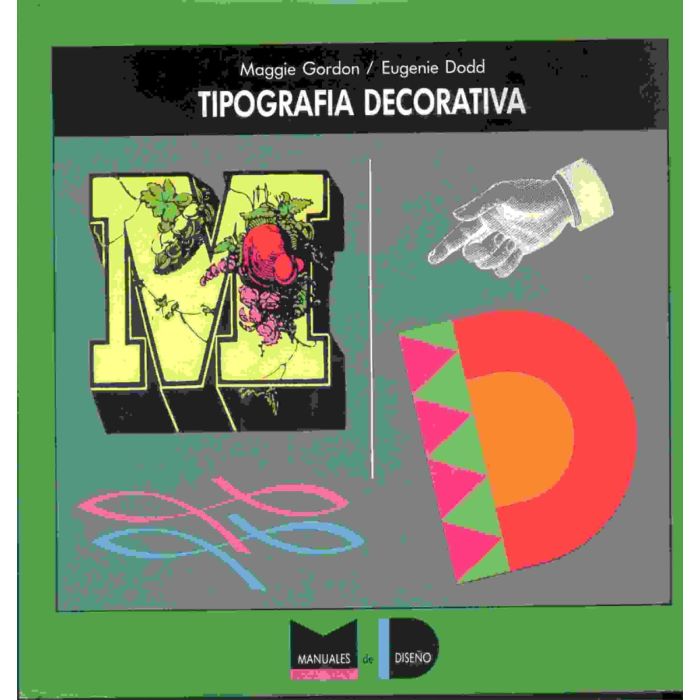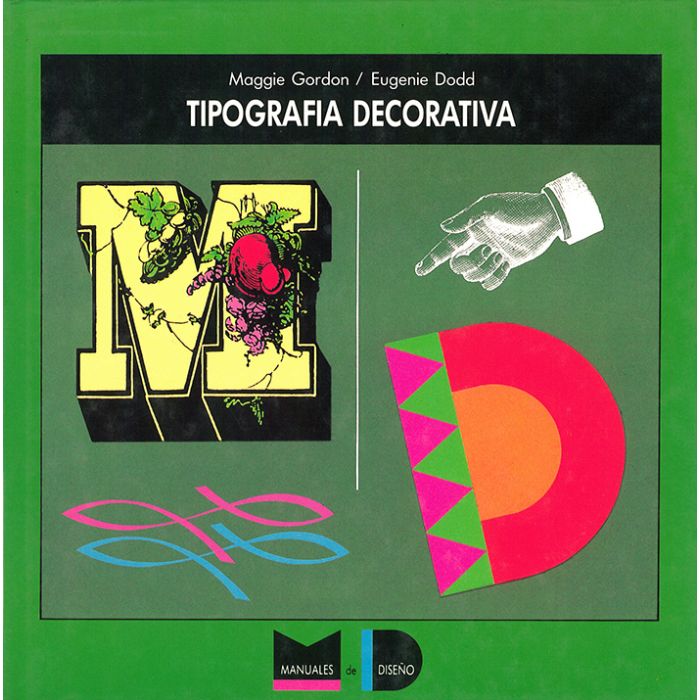
Tipografía decorativa
La tipografía es una de las primeras prácticas del diseño que se puede dominar y tambien es una de las más difíciles. Un conocimiento claro de sus posibilidades es esencial si se quiere sacar el máximo partido de cualquier diseño.
Tiografía decorativa muestra precisamente cómo introducir rúbricas y adornos para dar un toque de estilo individual y de personalidad a un determinado tipo de letra. Se cubren todas las posibilidades, desde la introducción de una simple línea hasta el uso de mayúsculas decarativas y el potencial de los sombreados y negativos, y se muestran los espectaculares efectos de diseño que se pueden producir.
La tipografía es una de las primeras prácticas del diseño que se puede dominar y tambien es una de las más difíciles. Un conocimiento claro de sus posibilidades es esencial si se quiere sacar el máximo partido de cualquier diseño.
Tiografía decorativa muestra precisamente cómo introducir rúbricas y adornos para dar un toque de estilo individual y de personalidad a un determinado tipo de letra. Se cubren todas las posibilidades, desde la introducción de una simple línea hasta el uso de mayúsculas decarativas y el potencial de los sombreados y negativos, y se muestran los espectaculares efectos de diseño que se pueden producir.